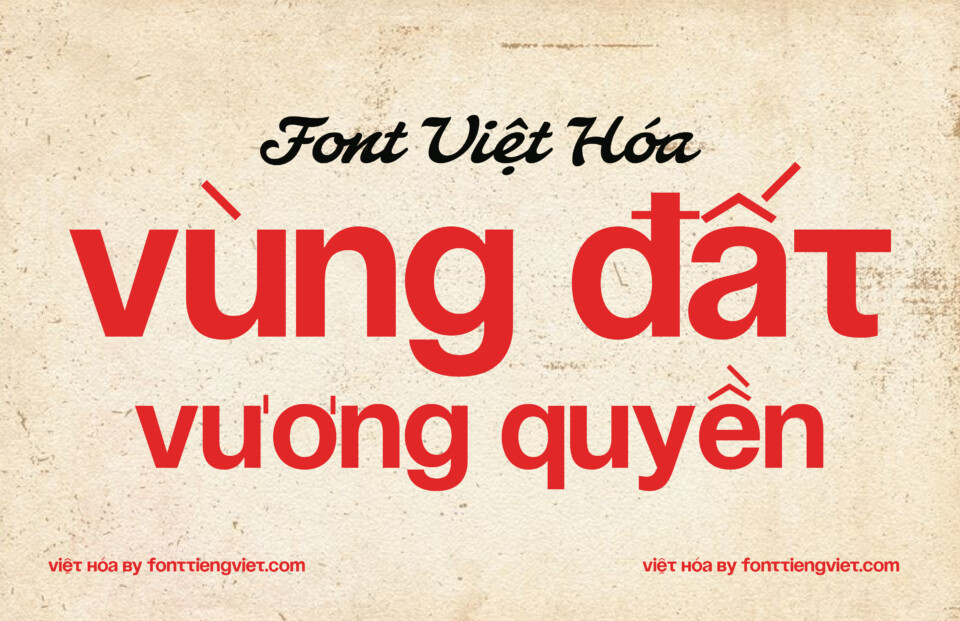
Font Việt hóa 1FTV VIP Soyuz Grotesk
Font Việt hóa 1FTV VIP Soyuz Grotesk – Lựa chọn hoàn hảo cho thiết kế đồ họa Việt
Giới thiệu về Font Việt hóa 1FTV VIP Soyuz Grotesk
Trong thế giới thiết kế đồ họa hiện đại, việc tìm kiếm một bộ font vừa mang đậm nét cổ điển vừa đảm bảo tính ứng dụng cao là điều không hề dễ dàng. Font Việt hóa 1FTV VIP Soyuz Grotesk chính là giải pháp lý tưởng cho những ai yêu thích phong cách Typography mạnh mẽ và quyết đoán. Đây là một bộ Font Miễn Phí được tinh chỉnh kỹ lưỡng về dấu tiếng Việt, giúp người dùng tại Việt Nam dễ dàng sử dụng trong các dự án sáng tạo mà không lo lỗi hiển thị. Với cấu trúc hình học đặc trưng, Soyuz Grotesk gợi nhắc về những áp phích cổ động thế kỷ trước nhưng vẫn giữ được hơi thở đương đại, phù hợp cho nhiều mục đích từ in ấn đến truyền thông số.
Đặc điểm nổi bật của Font Việt hóa 1FTV VIP Soyuz Grotesk
Thiết kế đậm chất Brutalist và Grotesque
Font Việt hóa 1FTV VIP Soyuz Grotesk mang phong cách thiết kế không chân (sans-serif) với các nét chữ dày, dứt khoát và có độ tương phản thấp. Sự tối giản này tạo nên cảm giác vững chãi và chuyên nghiệp cho văn bản. Đặc biệt, bộ font này loại bỏ các chi tiết thừa, tập trung vào sự rõ ràng của mặt chữ, giúp người xem dễ dàng tiếp nhận thông tin ngay từ cái nhìn đầu tiên. Khả năng hiển thị tốt trên cả màn hình máy tính và thiết bị di động là một điểm cộng lớn khiến bộ font này được nhiều designer ưa chuộng.
Khả năng tương thích tuyệt vời cho người dùng Việt
Vấn đề lớn nhất khi sử dụng các font chữ quốc tế là lỗi dấu tiếng Việt như “đ”, “ơ”, “ư” hoặc các dấu thanh bị lệch vị trí. Tuy nhiên, với phiên bản Font Việt hóa 1FTV VIP Soyuz Grotesk, mọi chi tiết đã được căn chỉnh hoàn hảo. Các dấu thanh được thiết kế đồng nhất với độ dày của nét chữ, tạo nên sự hài hòa tổng thể cho đoạn văn bản. Điều này rất quan trọng đối với các bạn học sinh, sinh viên khi làm báo cáo, slide thuyết trình hoặc thiết kế tập san trường học, giúp sản phẩm trông chỉn chu và có tính thẩm mỹ cao hơn.
Ứng dụng thực tế của bộ font trong đời sống
Sáng tạo nội dung và thiết kế truyền thông
Bạn có thể sử dụng Font Việt hóa 1FTV VIP Soyuz Grotesk cho các tiêu đề lớn, banner quảng cáo hoặc bìa sách. Nhờ vẻ ngoài nổi bật, bộ font này giúp thông điệp của bạn trở nên quyền lực và thu hút hơn. Trong môi trường giáo dục, thầy cô và học sinh có thể dùng font này để làm tiêu đề cho các bảng tin hoặc các dự án học tập mang tính chất tuyên truyền, cổ động. Ngoài ra, việc kết hợp Soyuz Grotesk với các font chữ có chân mảnh mai sẽ tạo ra sự đối lập thú vị, làm nổi bật các ý chính trong bài thiết kế của bạn.
Kết luận về bộ font chất lượng cao
Việc sở hữu một bộ font chữ đẹp và chuẩn Việt hóa sẽ giúp nâng tầm giá trị cho mọi tác phẩm sáng tạo của bạn. Font Việt hóa 1FTV VIP Soyuz Grotesk không chỉ đơn thuần là công cụ soạn thảo mà còn là nguồn cảm hứng để bạn thể hiện cá tính riêng. Nếu bạn đang tìm kiếm sự khác biệt và chuyên nghiệp, đừng ngần ngại tải ngay bộ Font Miễn Phí, Font Việt Hóa, Font Việt hóa 1FTV VIP Soyuz Grotesk này về máy. Hy vọng rằng những chia sẻ trên sẽ giúp ích cho cộng đồng thiết kế tại Việt Nam trong việc tiếp cận những tài nguyên đồ họa chất lượng và hoàn toàn miễn phí.